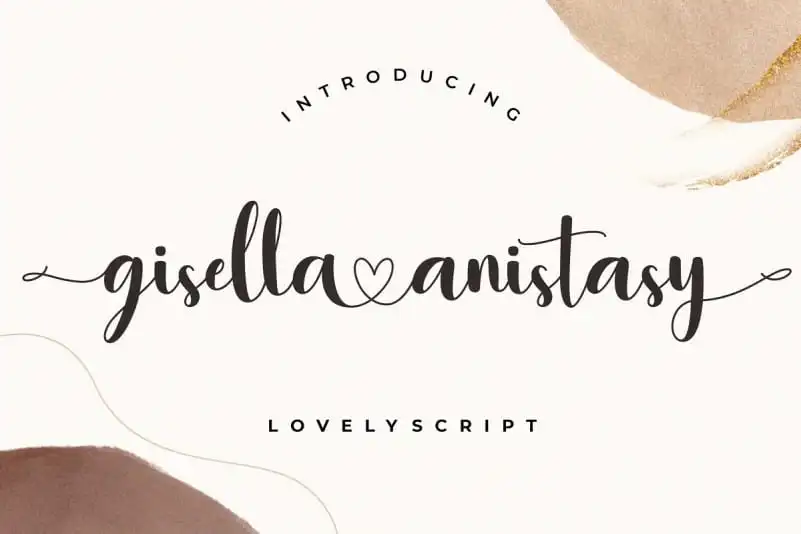
A Gisella Anistasy Script Font é uma elegante tipografia script criada pela Creatype Studio, disponível na categoria de fontes de escrita. Com seu aspecto moderno e sofisticado, esta fonte está projetada para se adaptar a uma variedade de aplicações criativas, desde o design de marca até as criações para embalagens de produtos ou materiais de convite. Seu charme elegante permite que você use essa fonte em um amplo leque de projetos, incluindo cartazes e anúncios, estilização de imagens fotográficas, assinaturas de água-marinha, convites para festas e até mesmo na produção de materiais de escrita. A Gisella Anistasy Script Font é uma escolha ideal para quem deseja dar um toque autêntico e pessoal a seus projetos gráficos. Seja você um profissional ou um amante da arte, certamente encontrará aqui uma fonte perfeita para atender às suas necessidades criativas.